서체 종류별 특징과 용도별 선택 기준
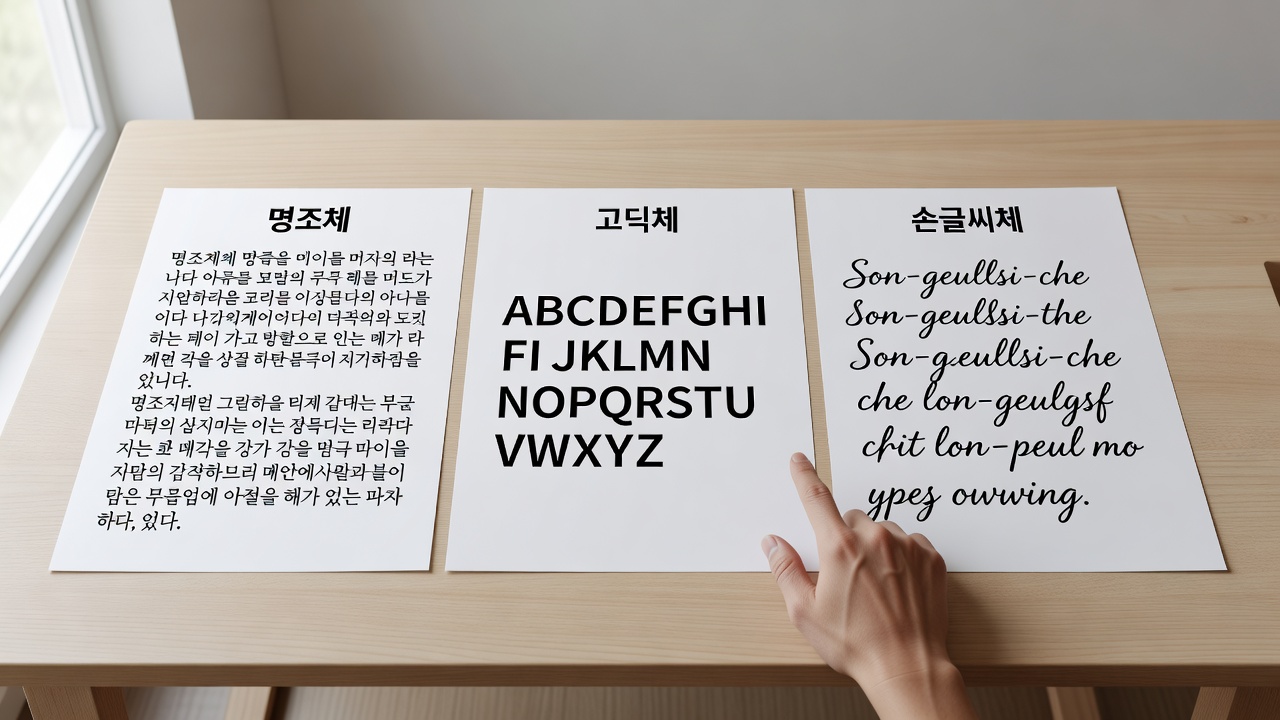
명조체는 본문 가독성에 강하고, 고딕체는 제목과 UI에서 명확한 전달력을 발휘하며, 손글씨체는 감성 콘텐츠에 적합하다. 프로젝트의 목적과 매체 특성에 따라 서체를 선택하는 것이 가장 중요하다.
서체 종류의 기본 분류
타이포그래피에서 서체는 크게 명조체, 고딕체, 손글씨체로 나뉜다. 각 서체는 획의 형태와 리듬이 다르며, 이는 독자가 텍스트를 인식하는 방식에 직접적인 영향을 준다. 2026년 현재 한글 타이포그래피 교육에서는 이 세 가지 분류를 기초로 프로젝트를 시작하는 경우가 일반적이다.
명조체는 세리프가 있는 전통적인 형태를, 고딕체는 세리프가 없는 깔끔한 형태를, 손글씨체는 필기체의 자연스러운 흐름을 특징으로 한다. 이 분류는 단순한 외형 구분을 넘어 콘텐츠의 성격과 독자 경험을 결정짓는 기준이 된다.
명조체의 특징과 본문 활용
명조체는 가로획과 세로획의 굵기 차이가 뚜렷하고, 글자 끝에 작은 장식이 붙어 있어 장시간 읽기에 유리하다. 신문, 소설, 학술 자료처럼 긴 문장을 다루는 매체에서 주로 사용된다.
한글 명조체는 자음과 모음의 균형이 중요하다. 과도한 장식은 오히려 가독성을 떨어뜨릴 수 있으므로, 본문용으로는 획의 두께와 간격이 적절히 조절된 서체를 선택해야 한다. 최근에는 디지털 환경에 최적화된 명조체들이 개발되어 모바일에서도 안정적인 읽기를 지원한다.
고딕체의 특징과 제목·UI 활용
고딕체는 획의 굵기가 일정하고 형태가 단순해 시각적 명확성이 높다. 제목, 버튼, 내비게이션 등 짧은 텍스트를 강조해야 하는 영역에서 효과적이다.
한글 고딕체는 자소 간 연결이 자연스럽고, 다양한 굵기 변형이 풍부하다는 장점이 있다. 2026년 현재 UI 디자인에서는 가변 폰트 형태의 고딕체를 활용해 화면 크기에 따라 유연하게 대응하는 사례가 늘고 있다.
손글씨체와 스크립트의 감성 표현
손글씨체는 필압과 속도의 변화를 담아 따뜻하고 개성 있는 분위기를 전달한다. 브랜딩, 카드 뉴스, 감성 에세이 등에서 주로 활용된다.
다만 손글씨체는 본문용으로는 피하는 것이 일반적이다. 획의 불규칙성이 장시간 읽기를 방해할 수 있기 때문이다. 제목이나 강조 문구에 제한적으로 사용하면 콘텐츠의 개성을 효과적으로 살릴 수 있다.
프로젝트 목적에 따른 선택 기준
| 용도 | 추천 서체 유형 | 주요 이유 | 주의점 |
|---|---|---|---|
| 긴 본문 | 명조체 | 가독성과 리듬감 | 장식 과다 금지 |
| 제목·헤드라인 | 고딕체 | 명확한 전달력 | 너무 얇은 굵기 피하기 |
| 감성 콘텐츠 | 손글씨체 | 따뜻하고 개성 있는 분위기 | 본문 사용 자제 |
| UI·앱 | 고딕체(가변) | 다양한 화면 대응 | 자간·행간 최적화 필요 |
한글 타이포그래피에서 주의할 점
한글은 자음과 모음이 결합하는 구조 때문에 영어와 다른 타이포그래피 고려가 필요하다. 특히 자소 간 간격과 균형이 무너지면 전체적인 인상이 크게 달라진다.
또한 한글 서체는 완성도에 따라 같은 계열이라도 품질 차이가 크다. 교육 자료나 공식 문서에서는 검증된 서체를 사용하는 것이 안전하다.
추천 도구와 리소스
2026년 현재 한글 타이포그래피 작업에 자주 쓰이는 도구로는 폰트 관리 프로그램과 온라인 서체 테스트 사이트가 있다. 실제 프로젝트에서는 미리보기 기능을 적극 활용해 최종 결과물을 확인하는 과정이 필수적이다.
명조체와 고딕체를 섞어 써도 되나요?
프로젝트의 계층 구조를 명확히 할 때 섞어 쓰는 것은 일반적인 방법이다. 본문은 명조체, 제목은 고딕체로 구분하면 가독성과 시각적 계층이 동시에 확보된다.
손글씨체를 본문에 사용해도 괜찮을까요?
짧은 분량의 감성 글이라면 가능하지만, 긴 본문에서는 피하는 것이 좋다. 독자의 피로도를 고려해 제목이나 인용구에 제한적으로 활용하는 편이 안전하다.
가변 폰트는 어떤 장점이 있나요?
하나의 파일로 여러 굵기와 스타일을 지원해 용량을 줄이고, 반응형 디자인에서 유연하게 대응할 수 있다. 2026년 현재 웹과 앱 프로젝트에서 선호도가 높다.
한글 서체 선택 시 가장 중요한 기준은 무엇인가요?
프로젝트의 목적과 독자 환경을 가장 먼저 고려해야 한다. 가독성, 브랜드 이미지, 기술적 호환성을 종합적으로 검토하는 것이 바람직하다.
결론